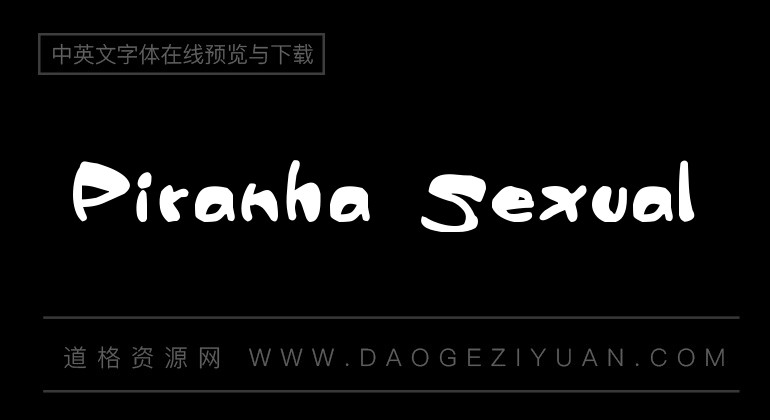
? Piranha Sexual是一款由英国设计师Chris Labrooy设计的独特的字体,它的特点是拥有抽象的曲线,拥有柔和的曲线,有流畅的线条,显示出激情和性感的气息。它的字体也具有艺术感,能够带来活泼的气氛,可以用于海报、标志、书籍封面等设计上。内容介绍
Piranha Sexual是一款非常不错的手写艺术字体,具有很好的视觉感,适合于文化类的宣传设计、商业类品牌的广告和产品包装设计以及个性化文字排版等较多场景。